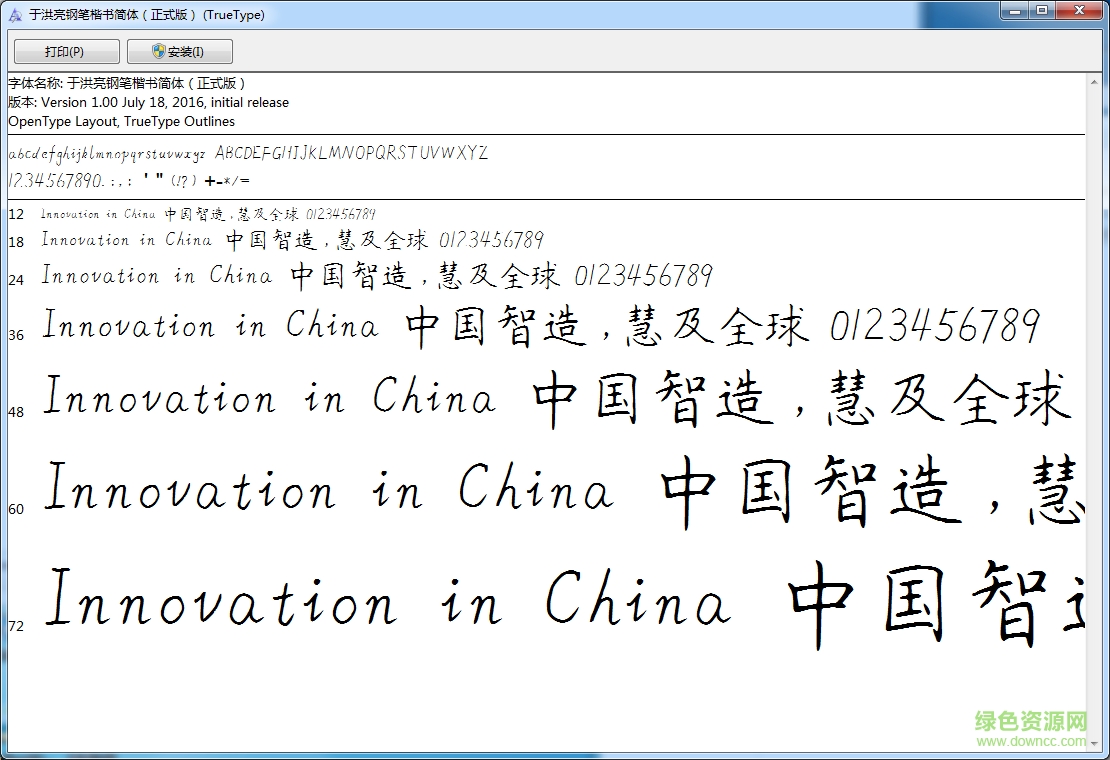
于洪亮鋼筆楷書簡(jiǎn)體
于洪亮鋼筆楷書簡(jiǎn)體是一款簡(jiǎn)單大方的鋼筆字體,字體端正簡(jiǎn)單極具個(gè)性,使用簡(jiǎn)單如行云流水一般。快來(lái)綠色資源網(wǎng)下載體驗(yàn)吧!
于洪亮鋼筆楷書簡(jiǎn)體介紹
于洪亮鋼筆楷書字體是一款非常不錯(cuò)的字體,字形強(qiáng)韌有勁并且?guī)в兴囆g(shù)氣息,非常適合鋼筆楷書設(shè)計(jì)方面,喜歡的用戶可以在本站進(jìn)行下載使用。